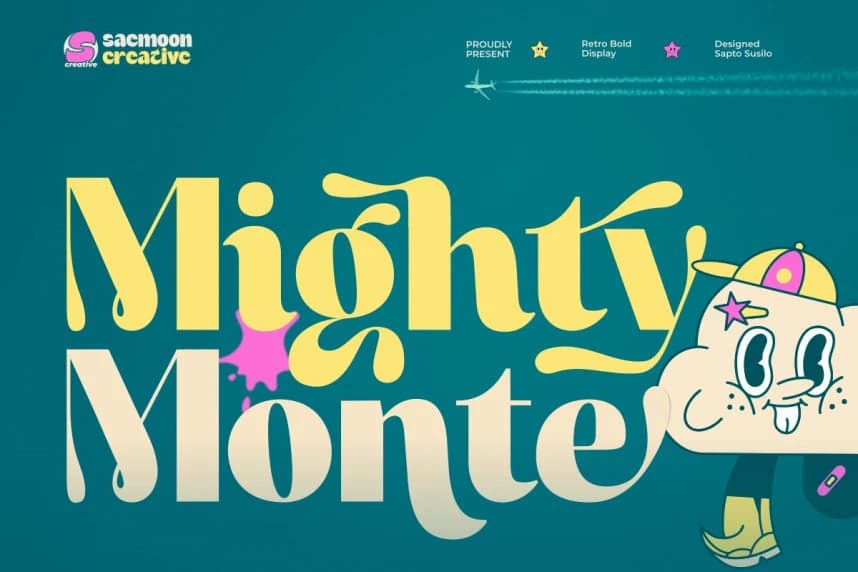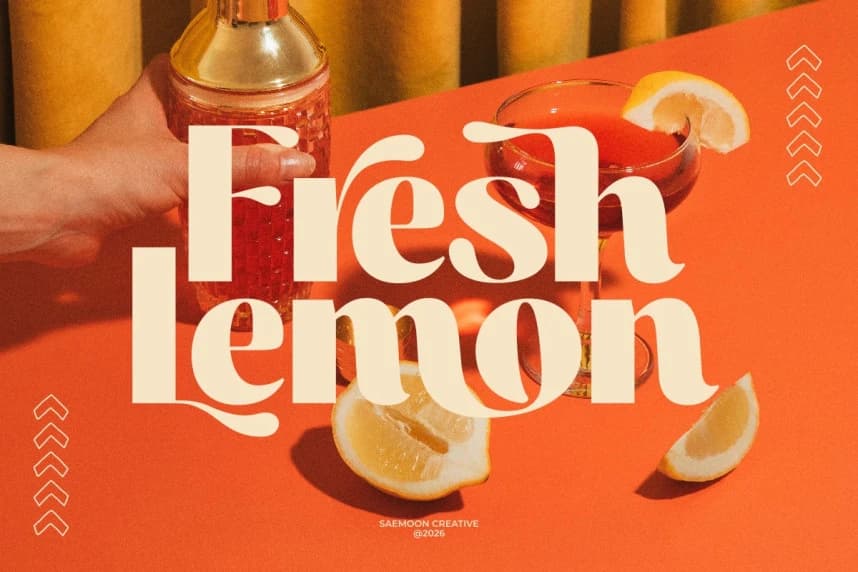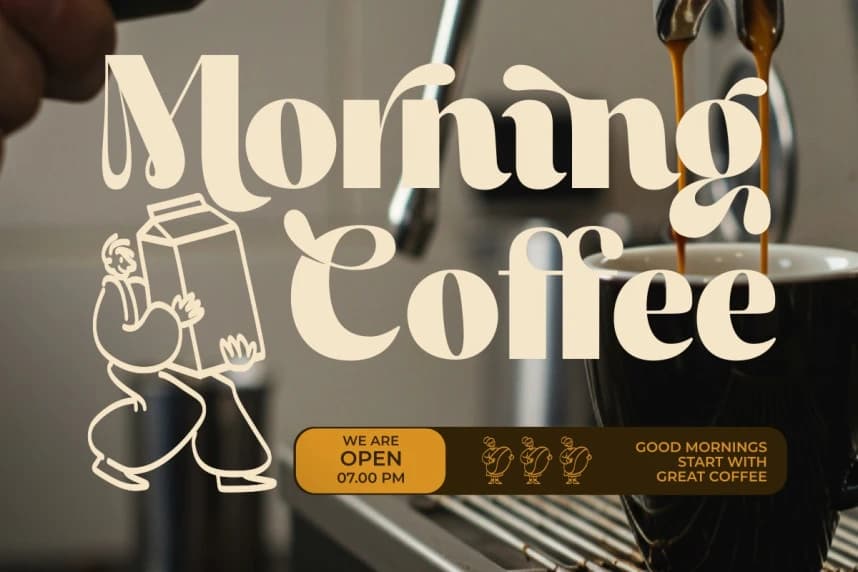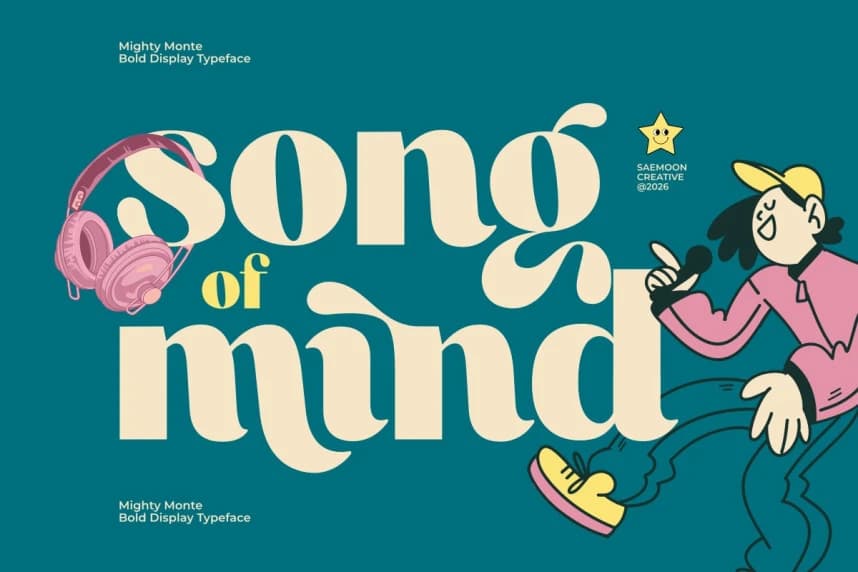
Mighty Monte Font
Mighty Monte Font, kalın şekiller, yumuşak eğriler ve çekici, tuhaf ayrıntılarla dolu oyuncu bir retro gösteri yazı tipidir. İşlerinize eğlence ve kişilik katmak için tasarlandı; bu yazı tipi, göz alıcı başlıklar ve ifade gücü yüksek tipografi yaratmak için mükemmeldir.
Mighty Monte Font, kalın şekiller, yumuşak eğriler ve hoş tuhaf ayrıntılarla dolu oynak bir retro gösterim yazı tipidir. İşinize eğlence ve kişilik katmak için tasarlandı; bu yazı tipi, dikkat çekici başlıklar ve ifade dolu tipografi oluşturmak için mükemmeldir.